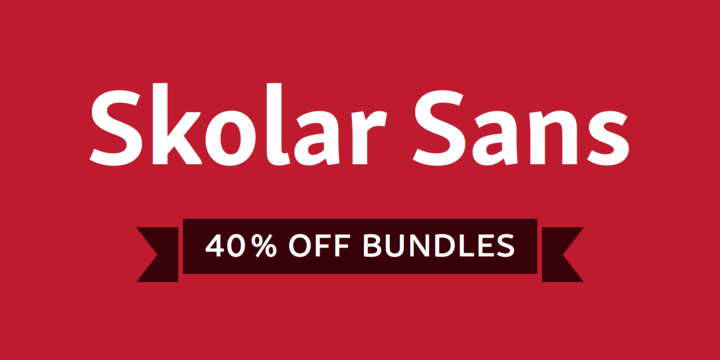
Die ist aber nett!
Falls es jemanden interessiert: die Adagio Serif gibt es derzeit bei MightyDeals für $17. Mit der Adagio Sans habe ich jetzt öfters gearbeitet. Das Hinting ist mangelhaft; am Monitor macht es also nur bedingt Spaß, aber ich finde die ja im Druck super, muß ich gestehen. Mal sehen ob es mit der Adagio Serif ähnlich ist.
Wow! Seit heute gibt es die Skolar Sans bei Myfonts und ein Schnitt kostet (Normalpreis!) nur 35,– Euro. Für eine mehrfach ausgezeichnete und hinsichtlich Schnittvarianten und Zeichenumfang bemerkenswert ausgebaute Schrift ganz schön moderat!
@CLMNZ: Deine AVERTA ist  identisch mit der bereits von @ROBERT genannten AVERSA (Schreibfehler).
Individuelle und charakterstarke Schriften zu zeichnen, die perfekt zu lesen sind und auch in langen Buchprojekten bestehen können, ist eine große Kunst. Mit der Book Design Collection erhalten Sie 13 Schnitte aus vier Familien von Type Together-Fonts, die als Basisausstattung für Ihre nächsten Buchprojekte keine Wünsche offen lassen. Profitieren Sie von der eleganten Renaissance Antiqua Essay Text, der lebendigen italienischen Antiqua Marco, der charmanten und persönlichen Pollen sowie der kalligrafischen Chancery Italic Alize.